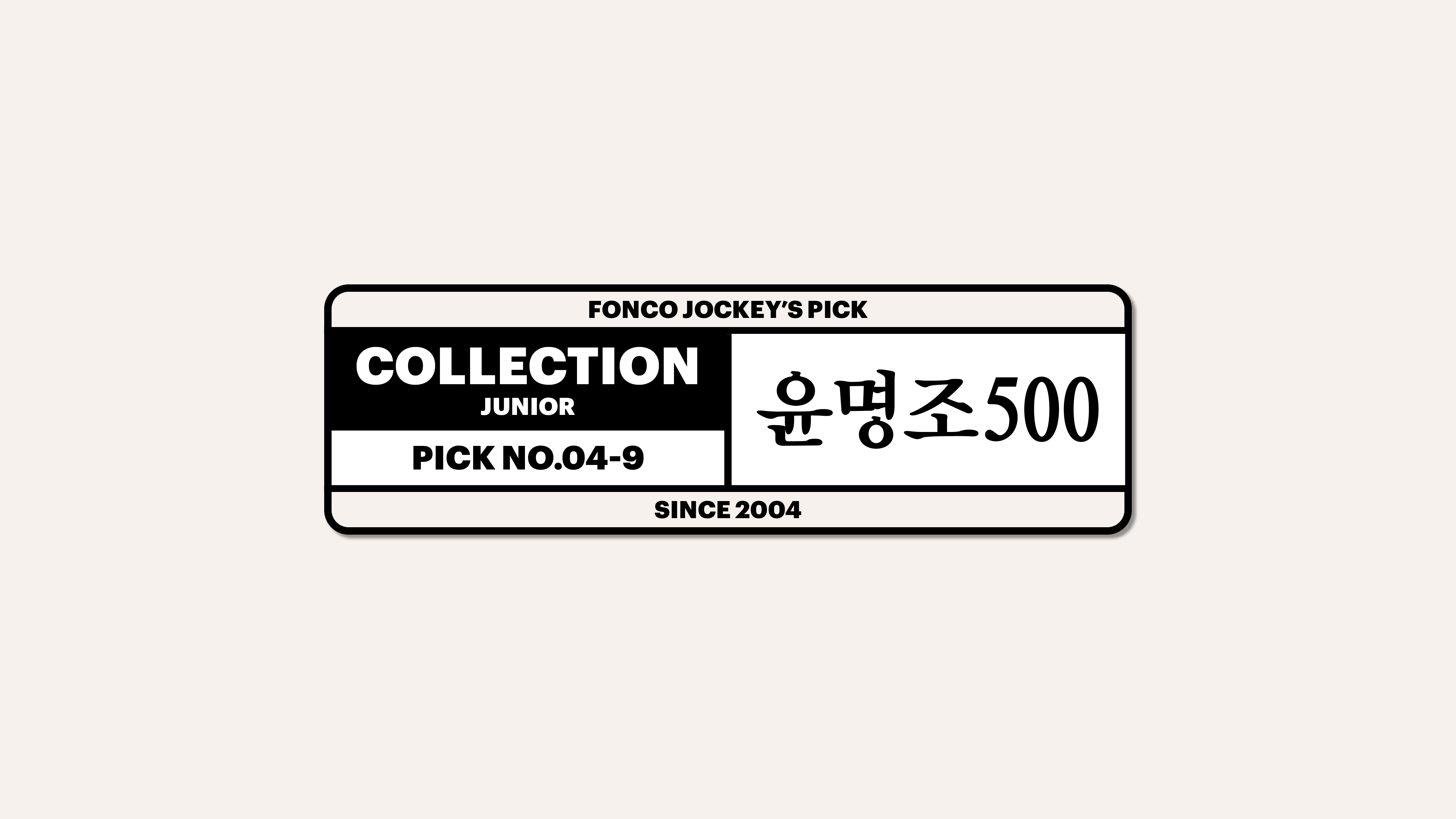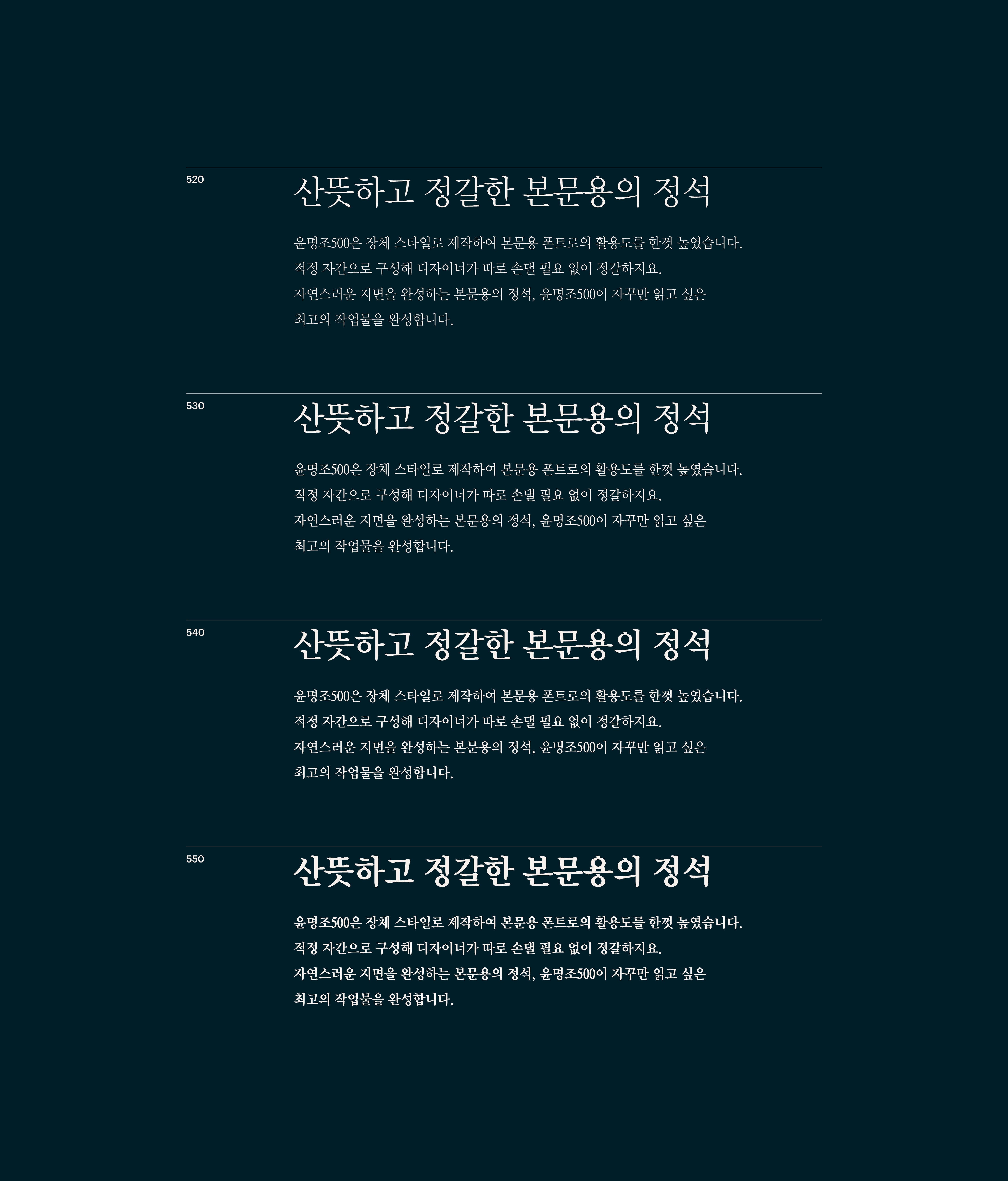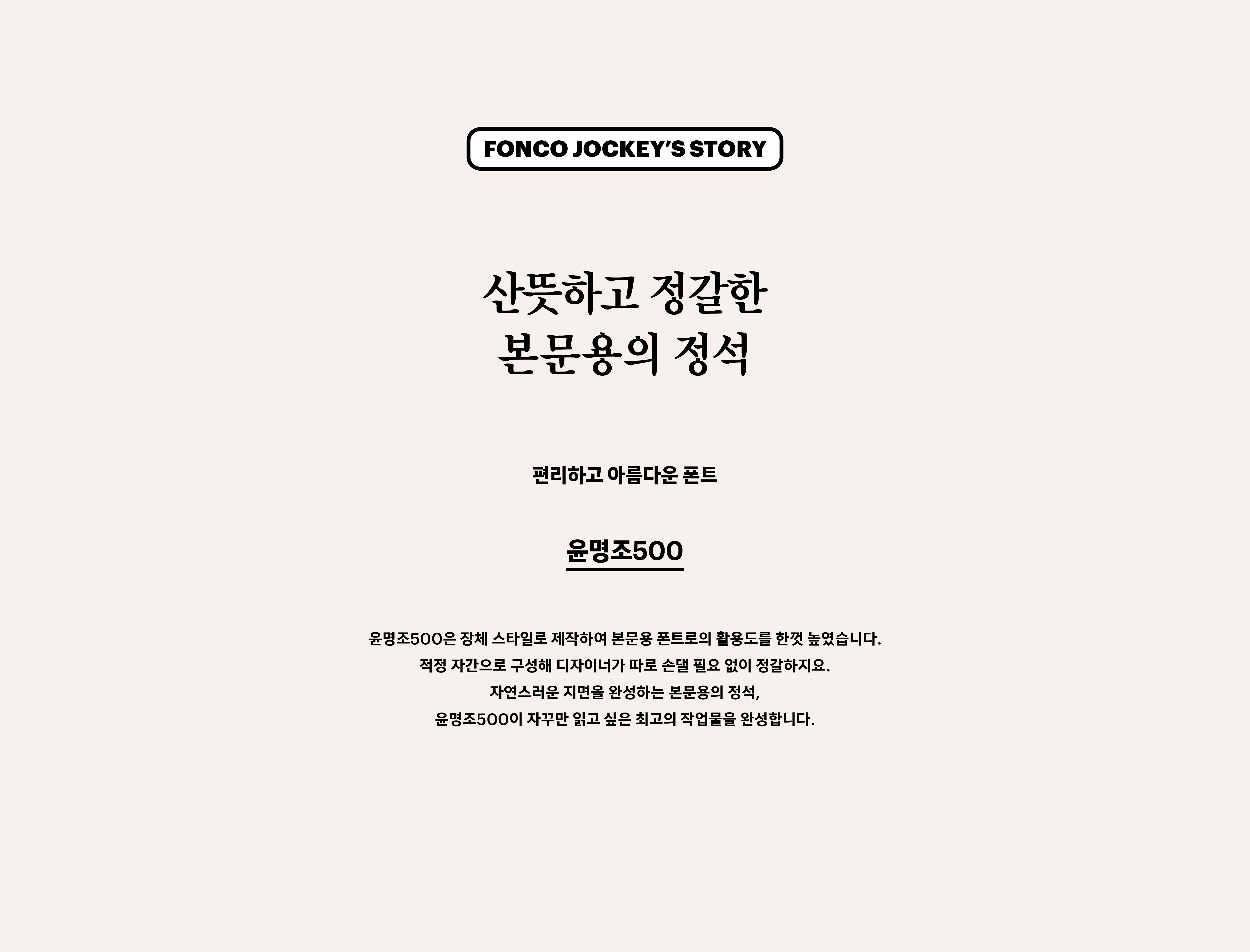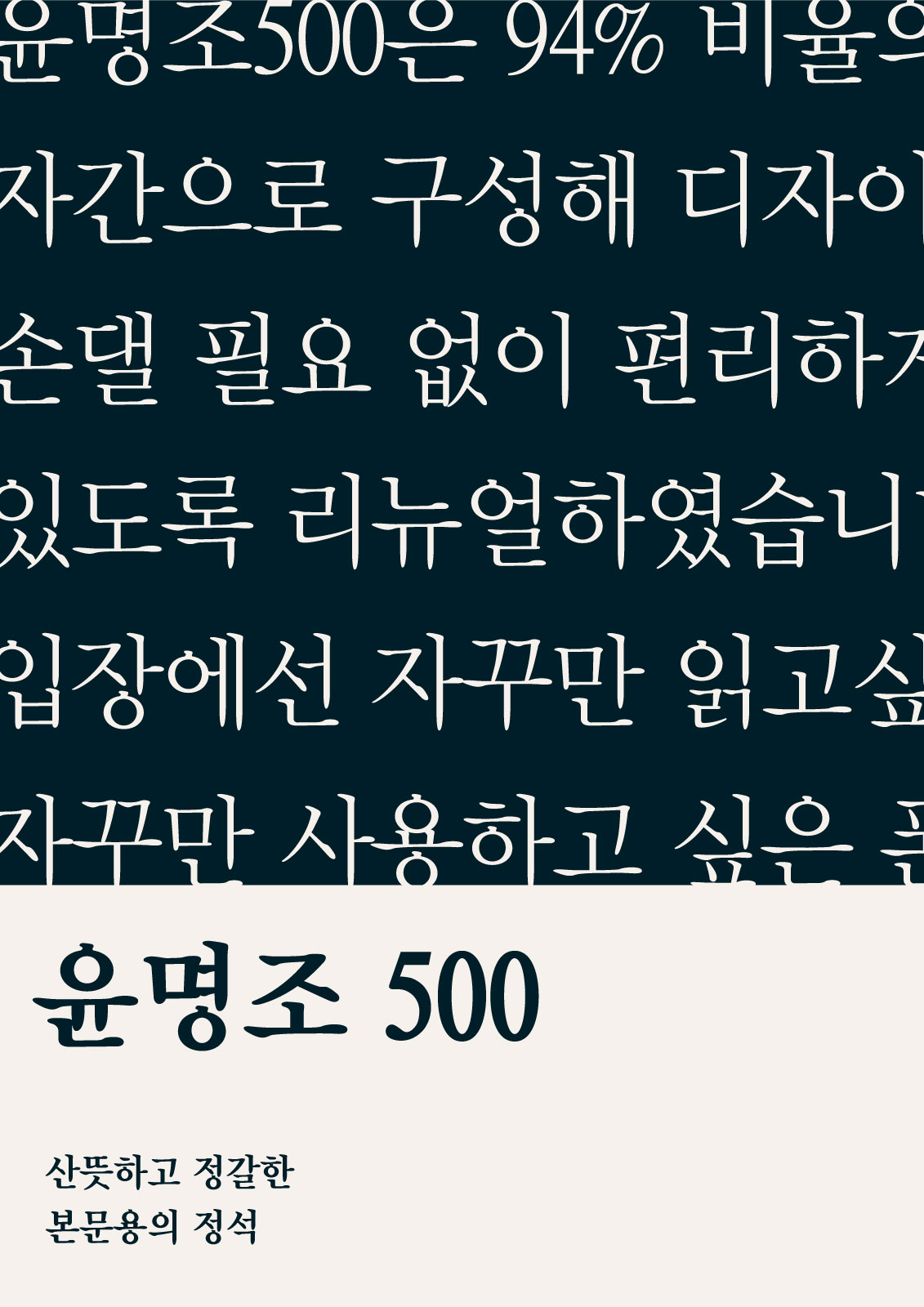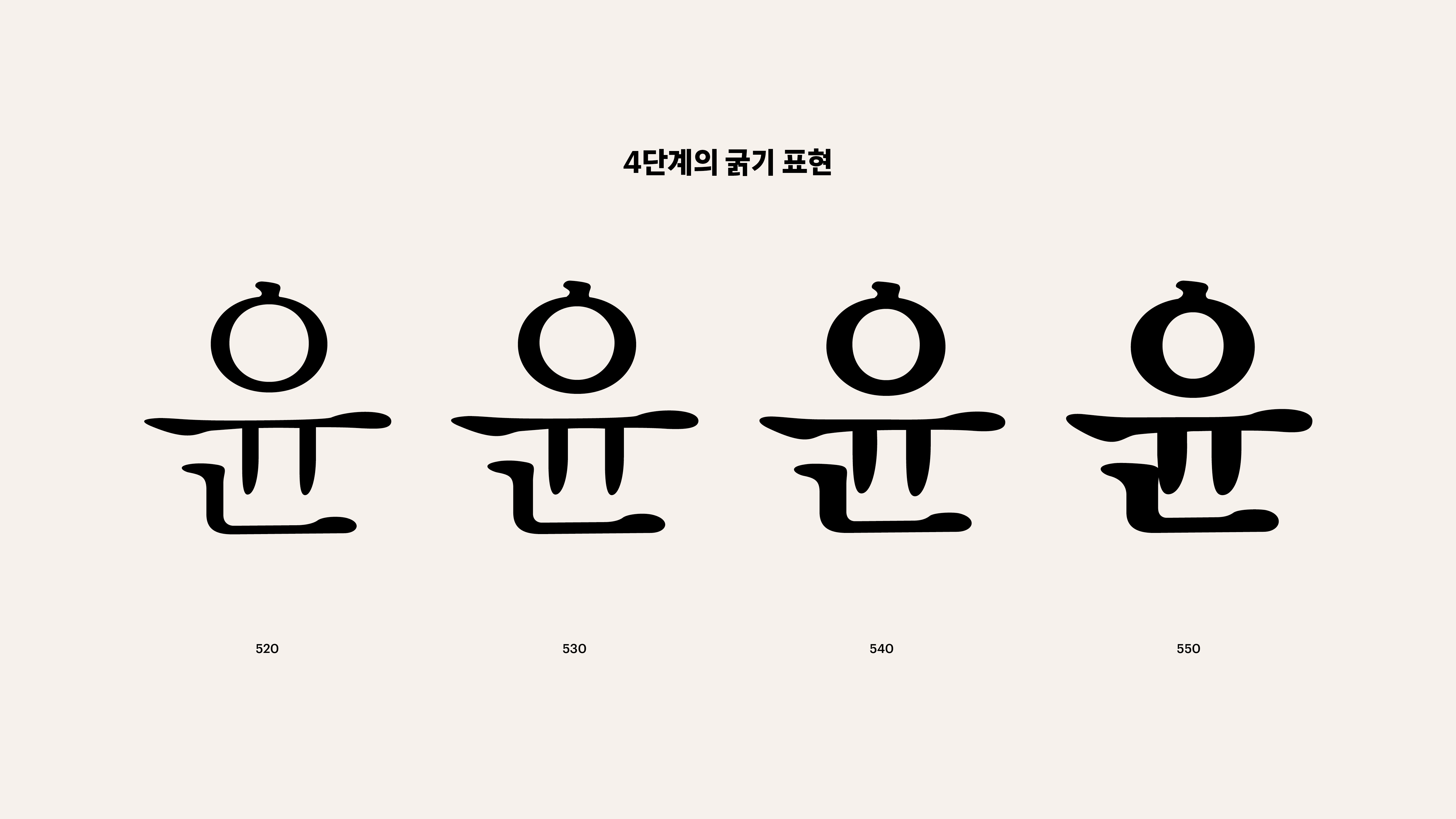
윤명조 500
Yoon 윤명조 500
윤명조500은 94% 비율의 장체, 적정 자간으로 구성해 디자이너가 따로 손댈 필요 없이 편리하게 사용할 수 있도록 리뉴얼했습니다. 독자 입장에선 자꾸만 읽고 싶은 폰트로, 디자이너의 입장에선 자꾸만 사용하고 싶은 폰트로. 변신을 거듭하고 있는 윤명조500. 어때요? 다음 행보도 기대되시죠?